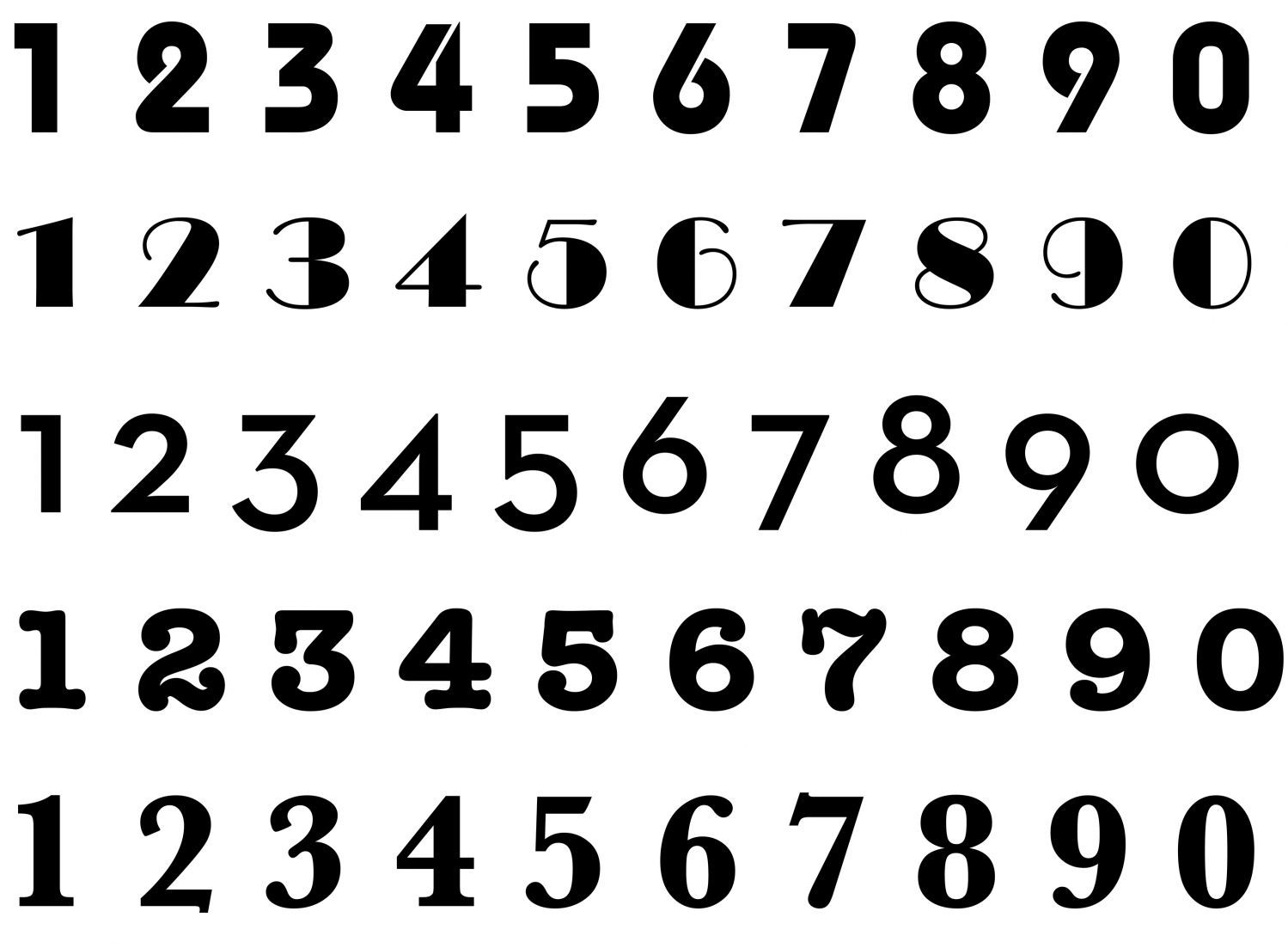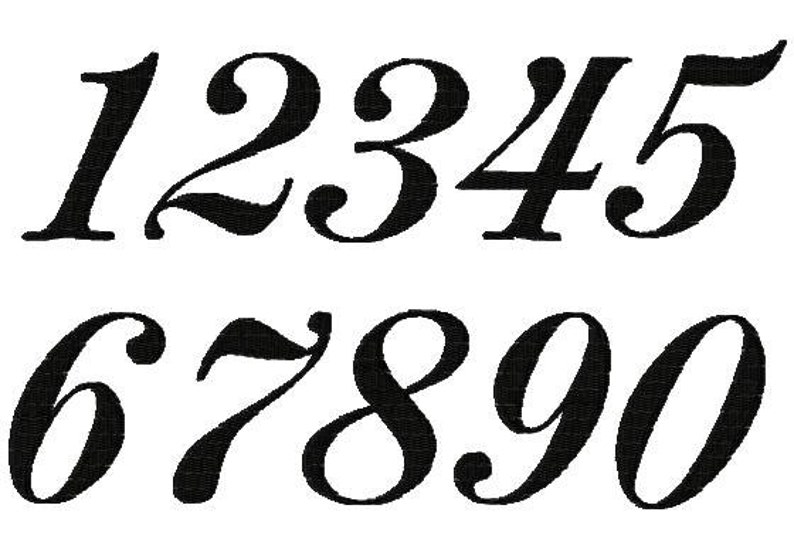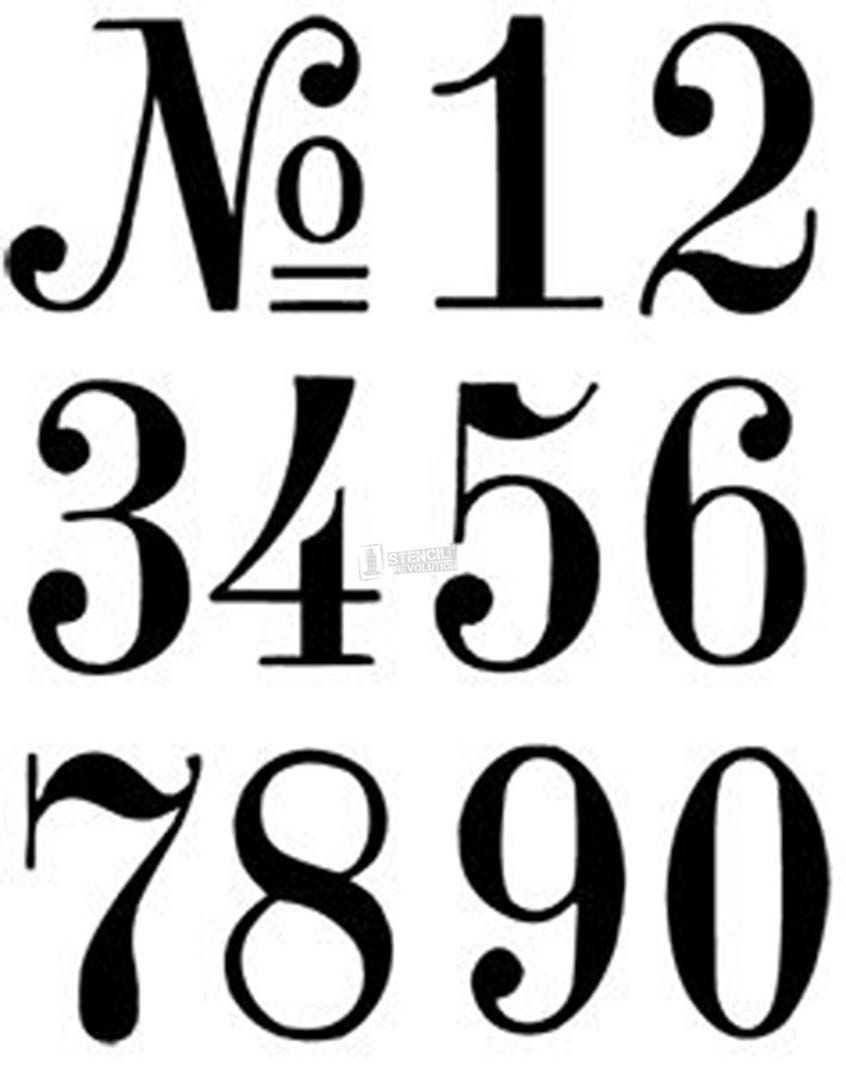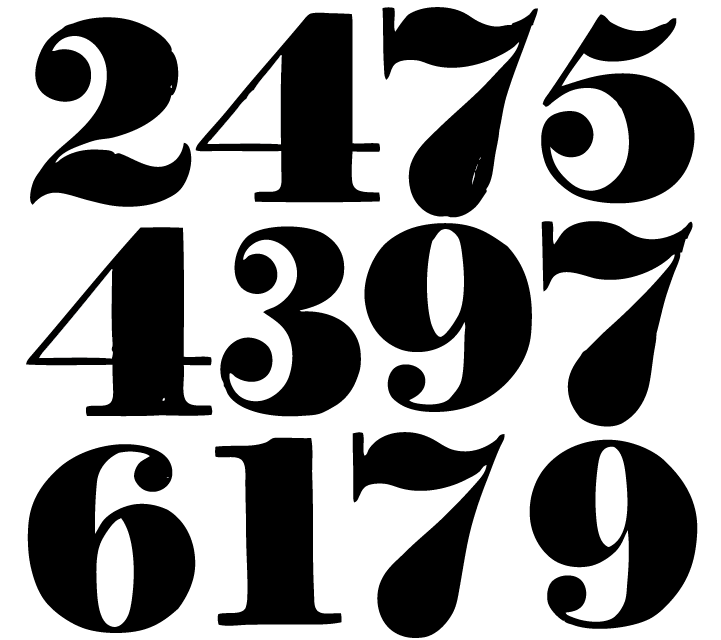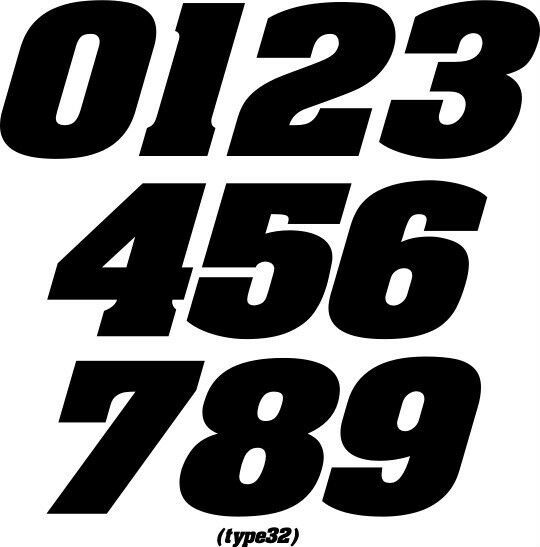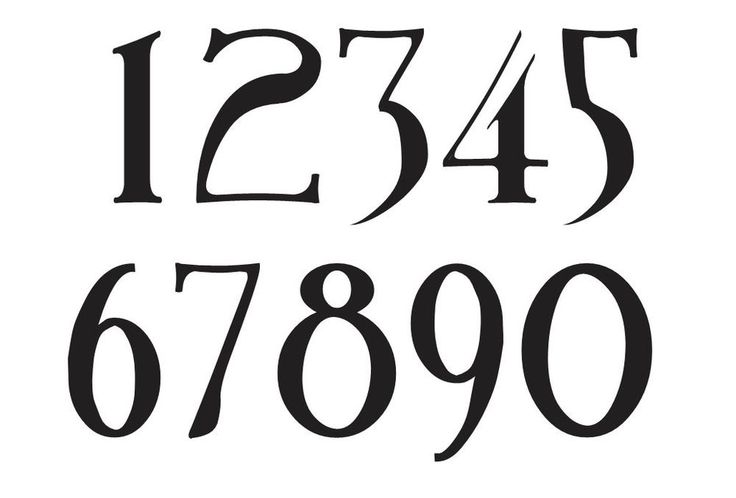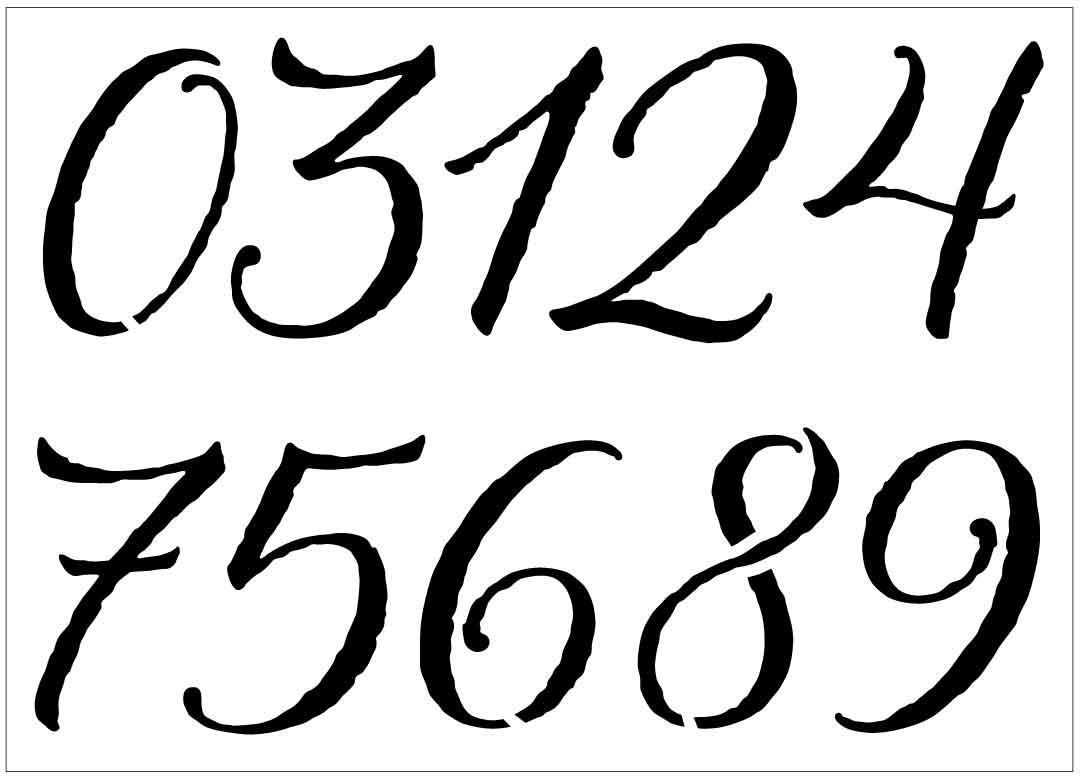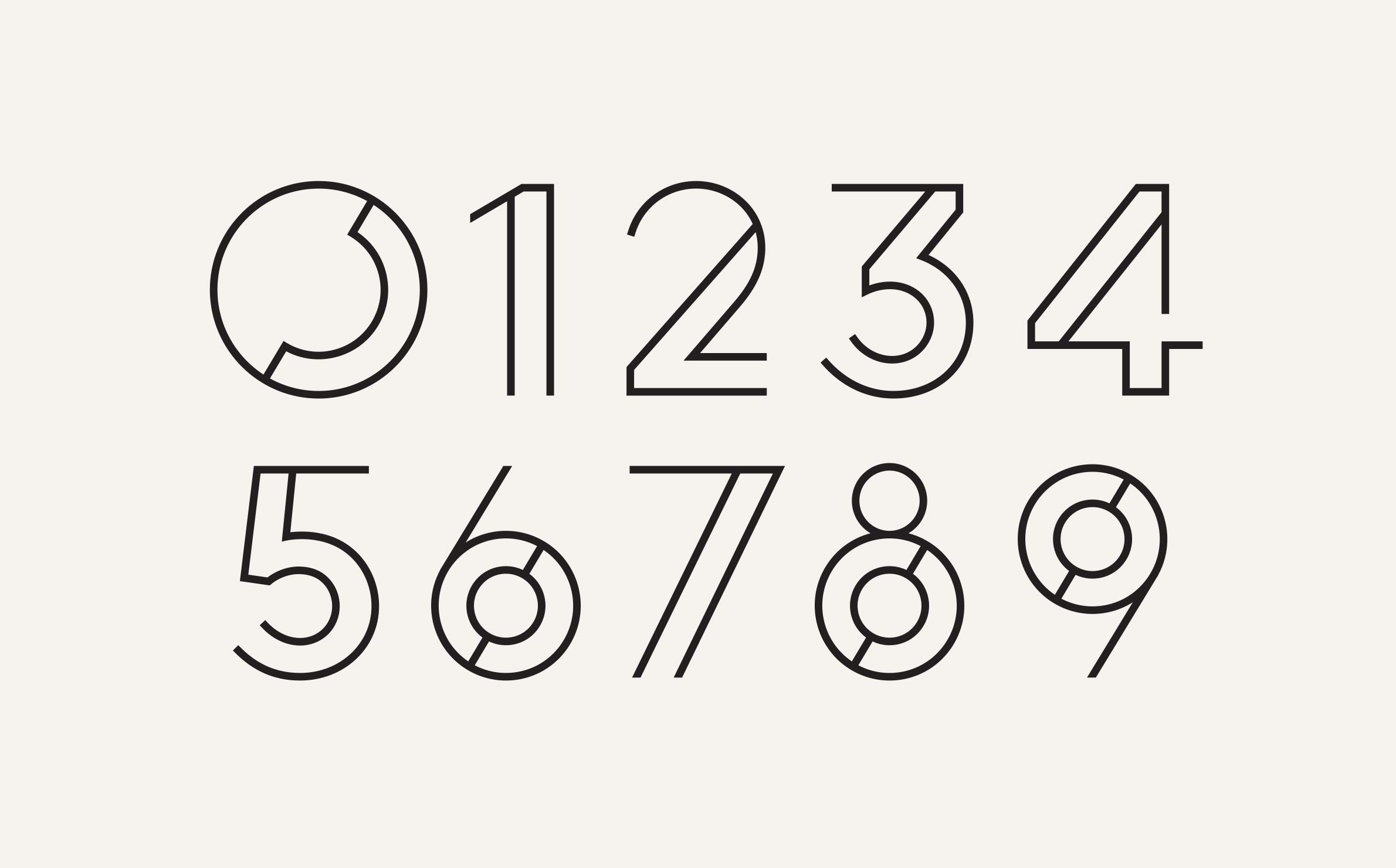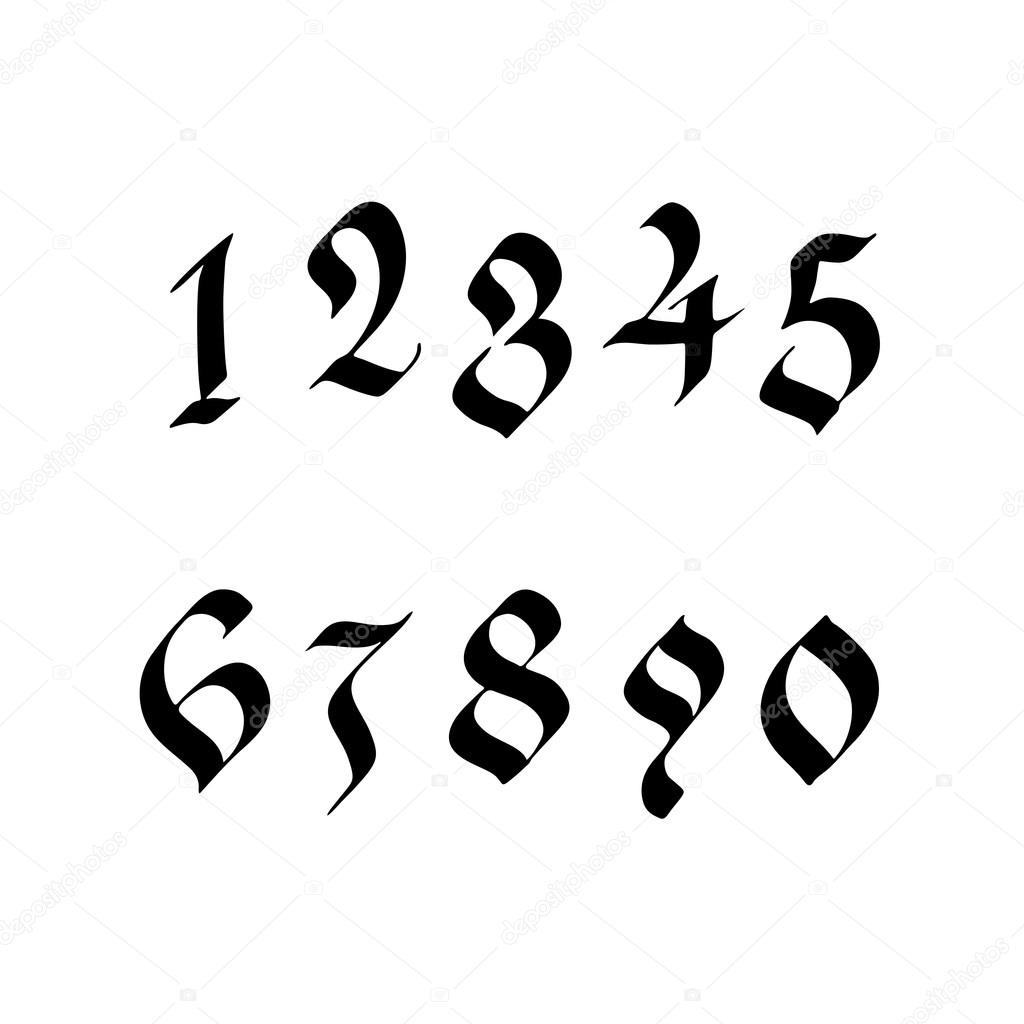
Генератор числовых шрифтов ς𝓸ρу ⓐℕ𝒹 p𝐚𝔰𝓣ε ➀❷𝟛
Генератор числовых шрифтов – Преобразование обычного текста в числовые стили шрифтов
Превратите простые числа в стильные числовые шрифты с помощью лучшего онлайн-генератора числовых шрифтов.
Он также предоставляет причудливый числовой шрифт с различными классными вариациями.
Все используют цифры в любом письме. Но что, если мы используем причудливый числовой шрифт, чтобы сделать простые числа более стильными и сделать наш контекст более привлекательным и запоминающимся? Чего же ты ждешь? Начните использовать безумное количество шрифтов в своих письмах, чтобы сделать их более эффективными. Если вы хотите сделать свои посты в социальных сетях эстетичными, используйте генератор эстетических шрифтов.